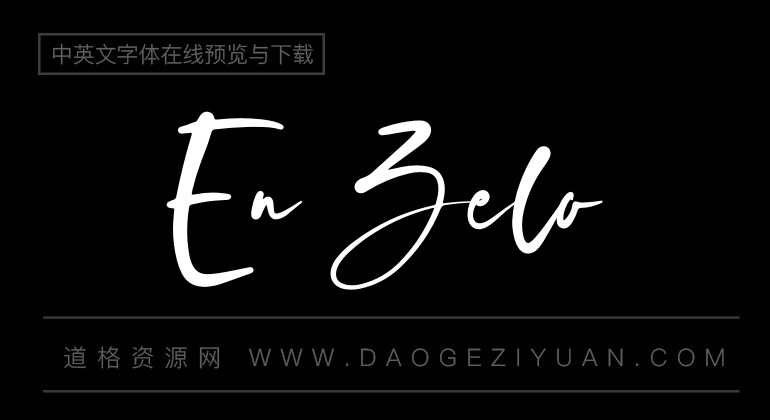
En Zelo 是一款由西班牙设计师 Javier Quintana 创作的字体,它是一款极简主义风格的字体,它具有清晰的线条和简洁的形式,以及精致的细节。En Zelo 字体可以用于任何类型的设计项目,特别是品牌标识,宣传海报和网页等。它还可以用于创建报纸,杂志,书籍,广告等。内容介绍
En Zelo是一款非常不错的手写艺术字体,具有很好的视觉感,适合于文化类的宣传设计、商业类品牌的广告和产品包装设计以及个性化文字排版等较多场景。